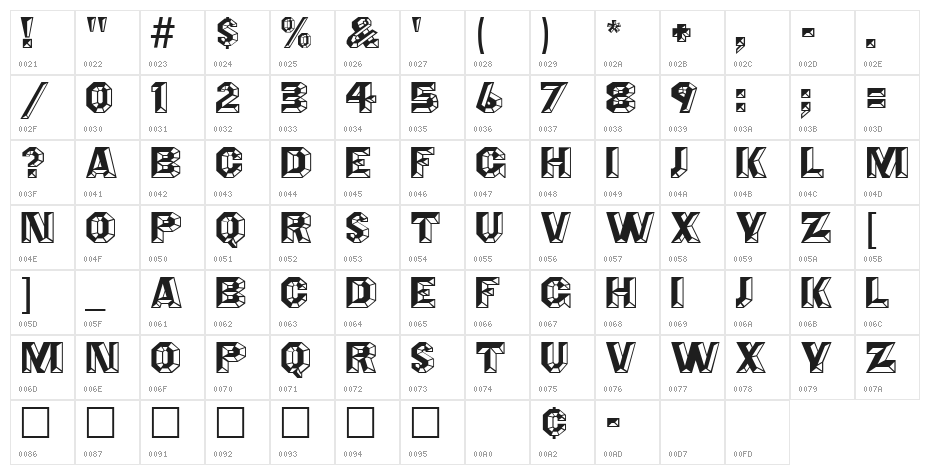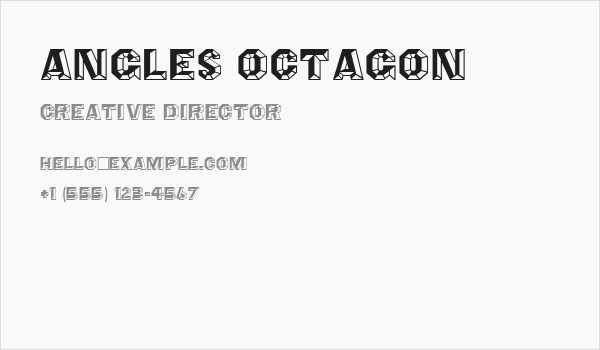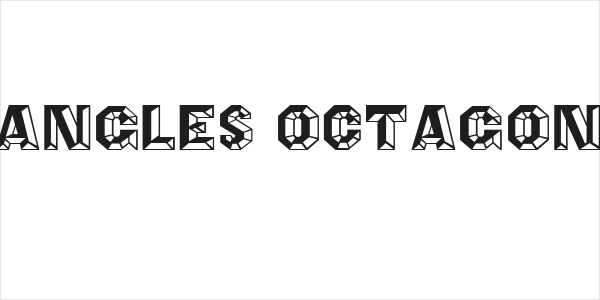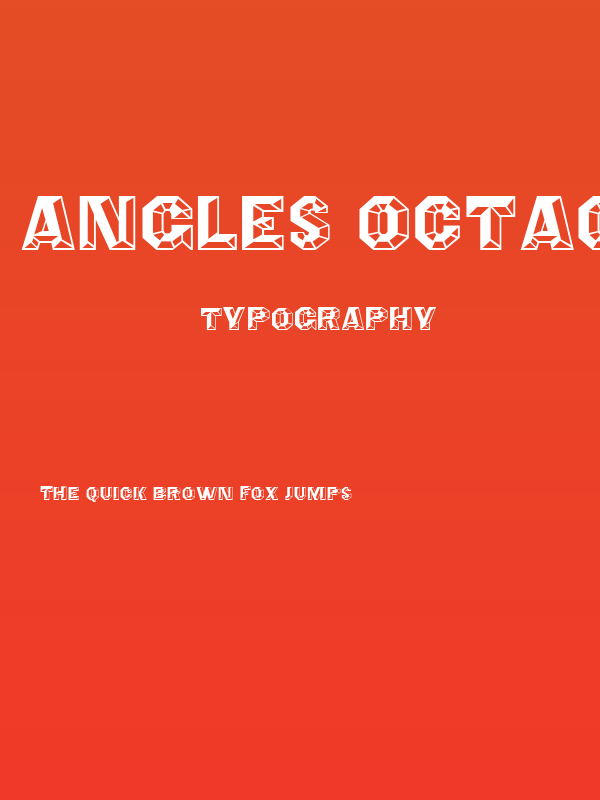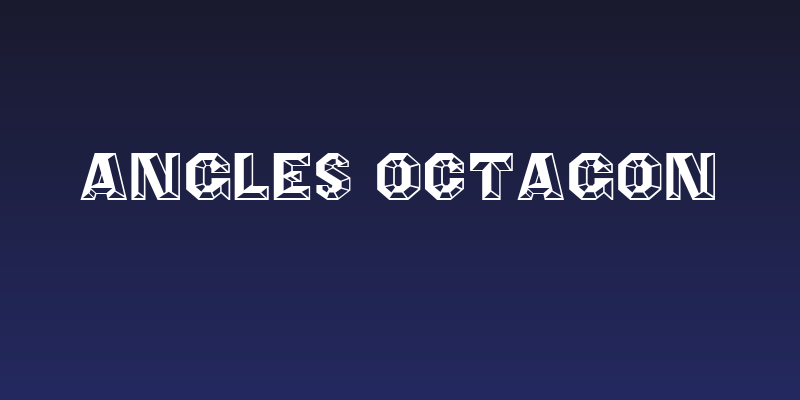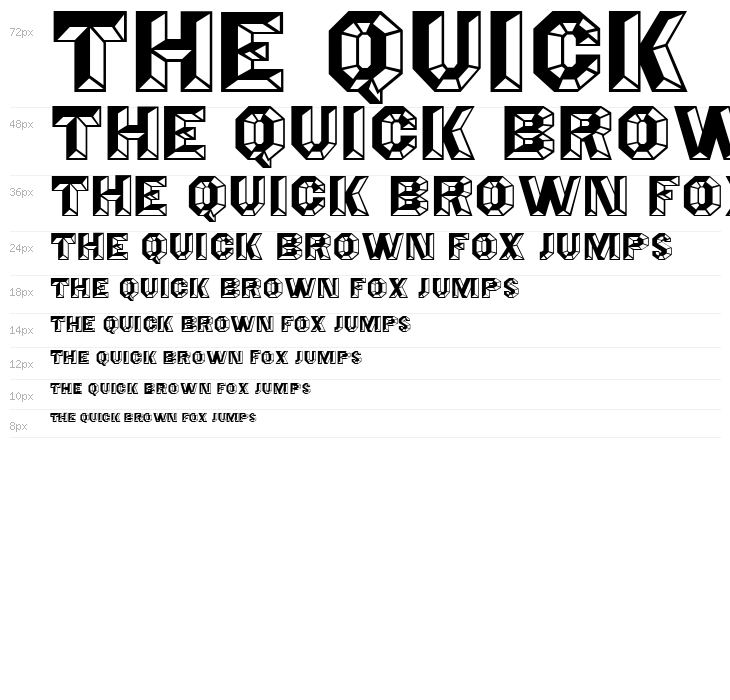
Angles Octagon Font
| Vorgeschlagene Projekte | Ideal for branding, poster design, album covers, and any project requiring a striking, modern aesthetic. |